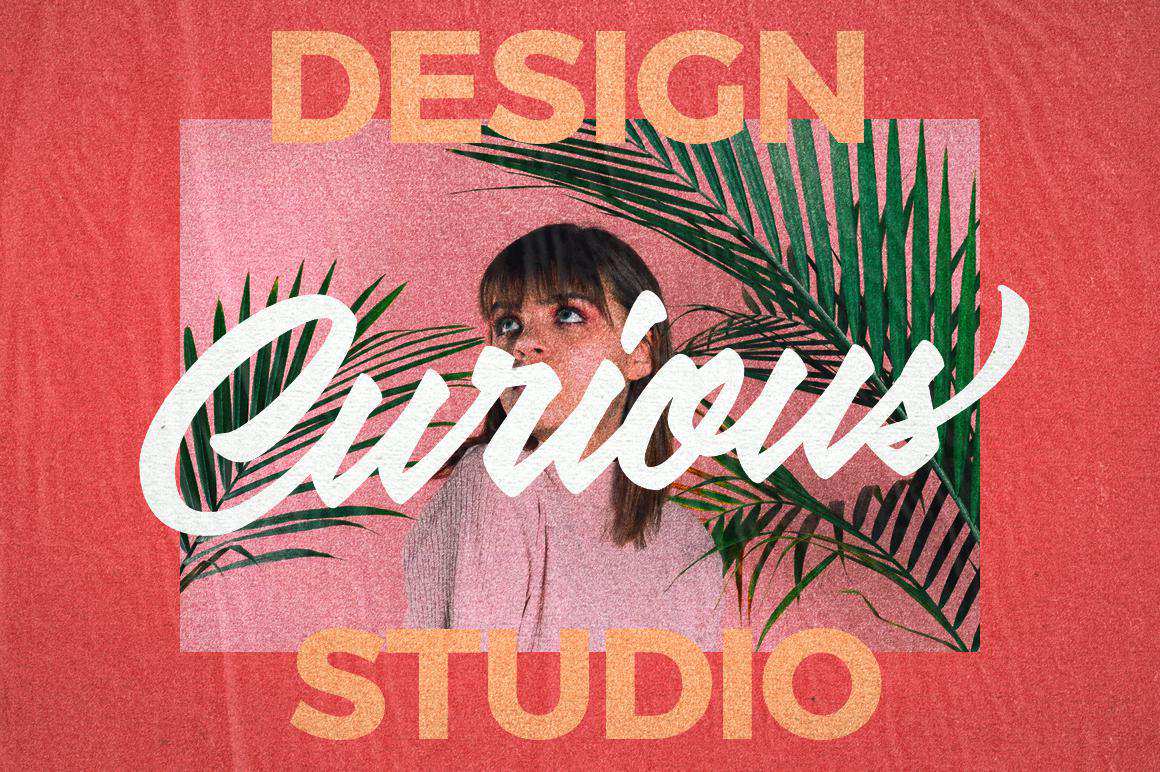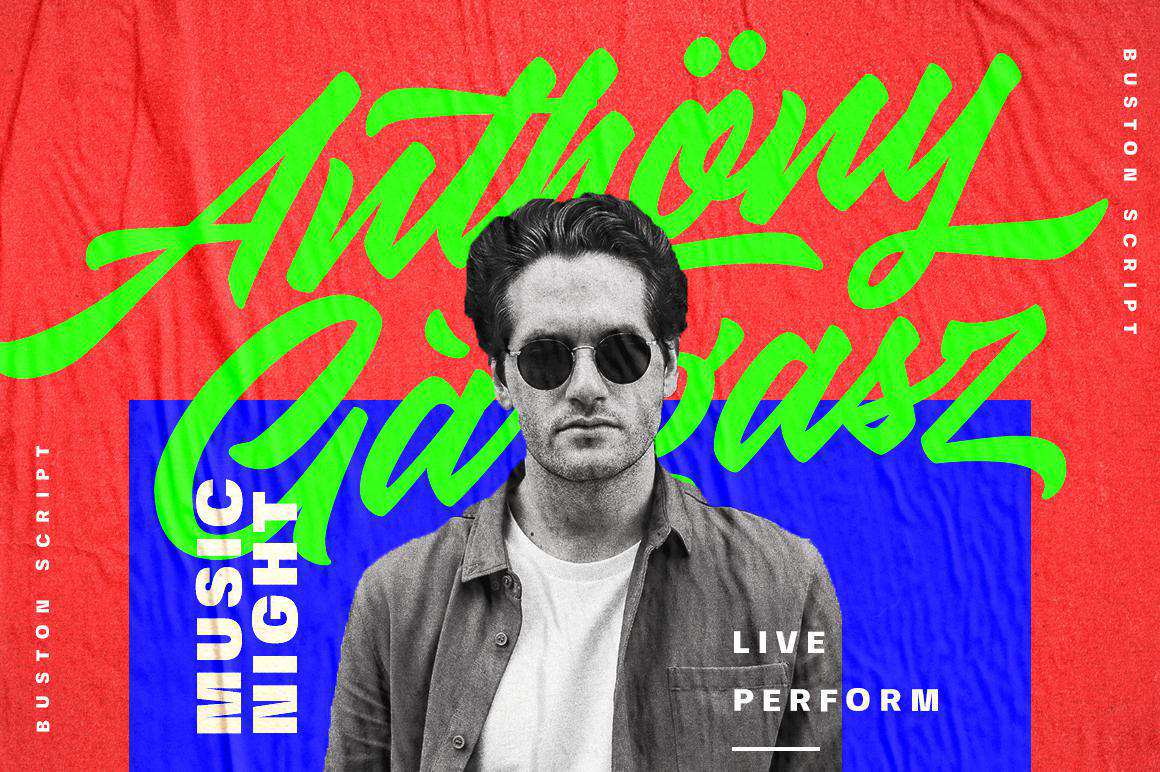
BustonScript受生活风格和时尚排版的启发。我将我的手写风格结合在一起。将个性融入到每一条曲线中。我希望这能让你从工作中获得灵感。每一条宽大的基线都有完美的修饰、修饰、修饰、修饰。理想的日志、手写引用、产品包装、标题、海报、商品,社交媒体和问候卡。BustonScript受生活风格和时尚排版的启发。我将我的手写风格结合起来。让个性化触动每一条曲线。我希望这能让你从工作中获得灵感。每一条宽大的基线都有完美的装饰性标记和超高的洗洁度。理想的日志、手写报价、产品包装,标题、海报、商品、社交媒体和问候卡。